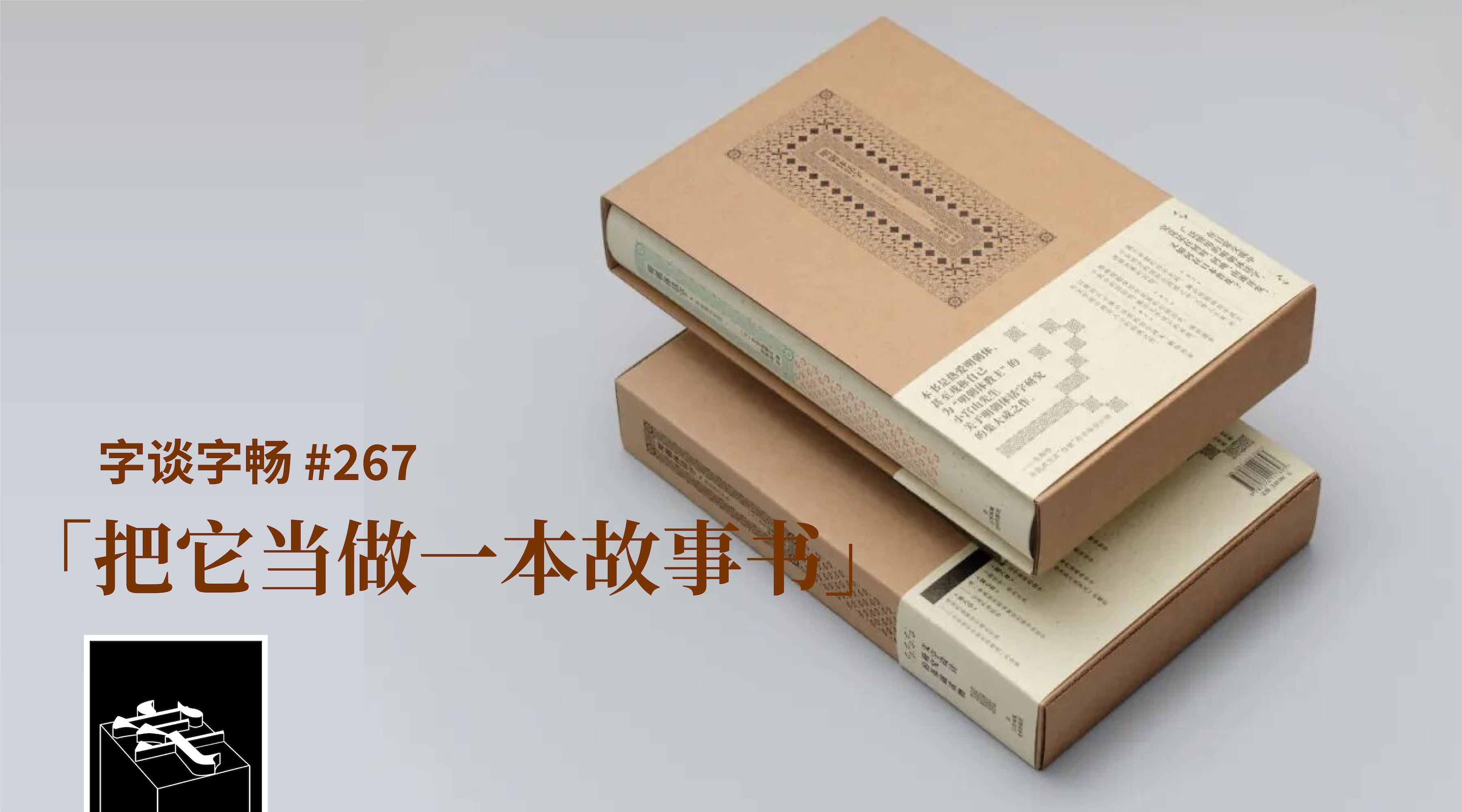
小宫山博史先生的《明朝体活字》,是日文明朝体设计史研究的重要专著。近日,其中译本付梓。我们有幸邀请译者孙明远老师,为大家介绍本书的脉络,及其背后的趣闻逸事。
- 小宮山博史.『明朝体活字—その起源と形成』.日:グラフィック社,2020 年
- 小宫山博史著,孙明远译.《明朝体活字:其起源与形成》.江苏凤凰美术出版社,2025 年
- 小宫山博史,日本字体设计及历史研究者,师从佐藤敬之辅;曾在武藏野美术大学、桑泽设计研究所、阿佐谷美术专科学校等执教
- 佐藤敬之辅,日本字体设计及历史研究者
- 府川充男,日本印刷史研究者
- 府川充男.『組版原論:タイポグラフィと活字・写植・DTP』.太田出版,1996
- 日下潤一,日本书籍设计师
- 日本字体排印学会
- 小宫山博史主办的系列讲座「 字体排印的世界」
- 位于东京的阿佐谷美术专门学校
- 孙明远(主编).《方寸之间——汉字文字设计文集》.文化艺术出版社,2023 年
- 方正 FW 筑紫古典明朝,方正字库、Fontworks 联合出品
- 孙明远:日本九州大学设计学博士,现任澳门理工学院副教授;中国及日本近现代平面设计史、字体排印史研究者